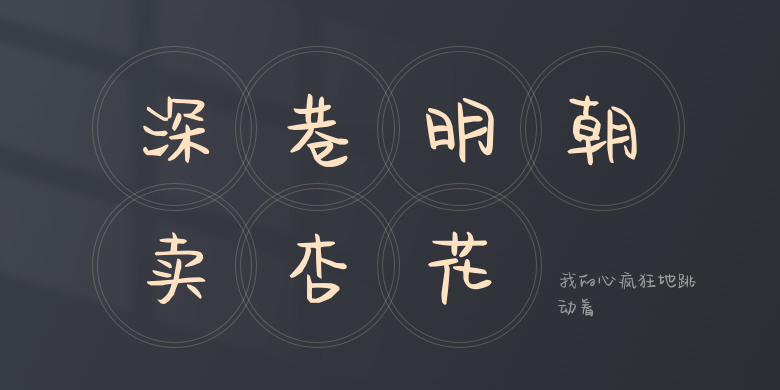
我的心疯狂地跳动着
我的心疯狂地跳动着,这款字体结构工整、笔画清晰,兼顾美观与易读性,适用于标题、正文、海报、包装、LOGO 等多种场景。字形优雅稳定,风格百搭耐看,适配日常排版与创意设计,让文字呈现更舒适、更具质感。我的心疯狂地跳动着一笔一画,皆是细节,以均衡的比例、流畅的线条打造舒适视觉体验,字形端正大气,风格简约现代。无论是商业设计、品牌宣传还是日常排版,都能轻松驾驭,让文字更有格调与力量。我的心疯狂地跳动着字体下载。